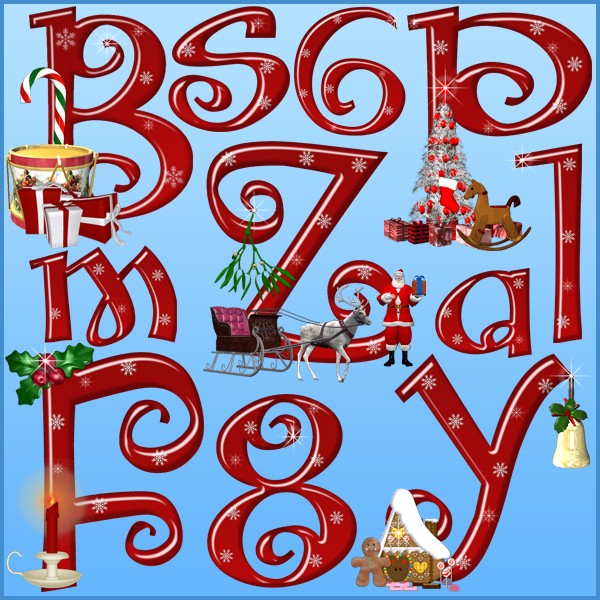
Рождественский латинский алфавит
Красивый красный латинский алфавит в высоком качестве включает в себя: заглавные буквы с различными рождественскими символами - Санта, ёлка, подарка, омела, эльфы, леденцы, олени, свечи, колокольчики; строчные буквы и цифры украшены снежинками.